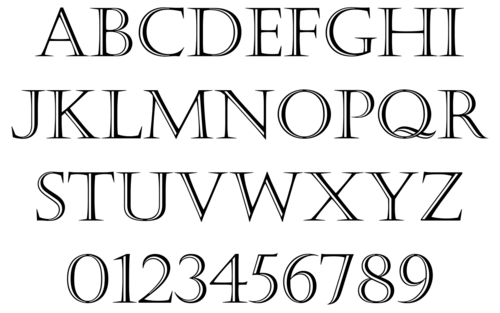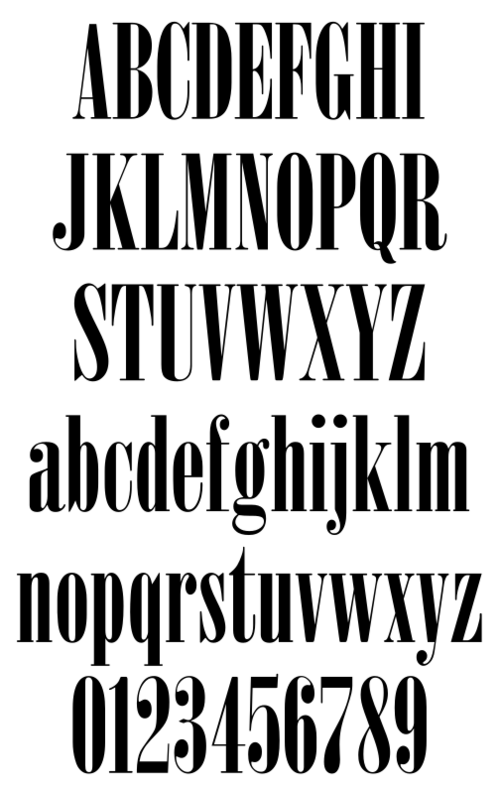
Monotype フォントはMonotype 社によって開発されました。この名前は 3 つの会社で使用されています。そのうち 2 つの会社は、印刷業界の「ホット メタル」または鉛活字にルーツを持っています。コンピューター、オフセット、写真システムが主流になって市場が変化しても、これらの会社は適応できませんでした。これらの会社は次のとおりです。
3 番目の会社は、コンピューターで使用するフォントを製造しています。
- モノタイプイメージング株式会社
後者の会社は、ある意味では英国のモノタイプ工場の後継者です。同社はオリジナルのデザインの権利を保有し、後に他の情報源からさらに多くのデザインの権利を取得しました。生産アーカイブの残骸とマシンの残骸は、英国ロンドンの活字博物館にあります。そこでは、オリジナルの母型に今でもアクセスでき、古いマシンの部品を注文できます。コレクション自体は大英科学博物館の所有物です。建物はもはや科学博物館の所有ではなく、修繕状態が非常に悪く、新しい所有者は建物を他の用途に使用しようとしていたため、活字博物館の存続が危ぶまれました。活字博物館は閉鎖され、すべての機器は国立公文書館に保管されています。[1]
熱い金属
上で述べた最初の 2 つの企業は、名前とシリアル番号で識別される多数のフォントを制作しました。その書体デザインは最終的に非常に評判が良くなり、「Monotype」ブランドは高品質と信頼性の代名詞となりました。[2]
彼らの名の下に、タイポグラフィの初期の歴史的な文字デザインに関する多くのタイポグラフィ研究が行われてきました。Garamond、Baskerville、Bodoni、Bembo、Caslonなどの多くの書体の文字を含む多くの文字が「復活」として制作されました。
両社の大きな違いは、アメリカのフォントが英語のフォントと一致しないことです。同じ名前の文字でもほとんどの場合デザイナーが異なり、外観や実装が異なります。識別番号はすべて一致しているわけではありません。
2 つの会社の母型は、深さ、母型内の画像、実装、およびサイズの点でも異なります。たとえば、アメリカの母型は 0.01 インチ (0.25 mm) 浅く、その結果、0.918 インチ (23.3 mm) の文字を印刷するには、アメリカの鋳造金型の内部を高くする必要があります。これは、2 つの Monotype 社が世界市場を分割するために取った多くの対策の 1 つです。たとえば、アメリカの会社は南北アメリカ大陸とカナダの市場にサービスを提供しました。イギリスの会社であるサルフォーズの Monotype Corporation Ltd. は、インド、アフリカ、およびアジアに多くの顧客を抱えていました。これらの国々向けに、ヘブライ語、ジャワ語、サンスクリット語、シンハラ語、タイ語、およびその他の言語の印刷用に、多くの非ラテン文字書体が作られました。
モノタイプ社の組版鋳造機は、1 片の活字で構成されたテキストを含む、すぐに使用できる組版ページを生成しました。この機械は、さまざまな幅のスペースを追加して行を揃え、行を塗りつぶしました。これらのエンディング マシンは、紙のリボンで制御されました。キーボードでテキストを入力するのは手作業で、鋳造よりもはるかに時間がかかりました。組版鋳造機には、少なくとも 3 つの個別のキーボードのリボンが必要でした。最終的な組版の修正は、可動式活字を交換するだけで済みました。Linotypeマシンのように、行を再鋳造する必要はありませんでした。
これらの組版鋳造機は、最大 14 ポイント パイカまたはディドー フォント幅の文字を生産できました。「大型組版」のカスタマイズされた機械と金型は、最大 36 ポイントの組版を提供できました。マトリックスはそれに応じて大きくなり、金型ケースには 1 つのアルファベットしか収まりません。このため、1 回の機械操作でローマン体とイタリック体の両方の書体の組版を提供することはできず、そのような場合には追加の手作業が必要でした。
手組版用の活字もモノタイプ機で鋳造されました。36 ポイントまでのすべての文字と罫線は、大型組版機で鋳造できました。もう 1 つの機械は「スーパー キャスター」または「スープラ」で、これは 1 つの活字を鋳造できました。改造後は、レグレット、装飾、類似のデザイン、および 72 ポイントまでの文字など、印刷所で必要なあらゆる素材の鋳造にも使用できました。14 ポイントから 36 ポイントのサイズ用のインサートを備えた鋳型がありました。さらに大きい 42、48、60、および 72 ポイントのサイズには、別の活字鋳造が使用されました。異なる活字要件ごとに機械を再構成する必要がありました。
ユニット配置
熱鉛モノタイプ活字の幅は、セット単位で表されます。アルファベットの最も幅の広い文字 (通常は大文字の「W」) は、1/4 パイカ ポイントで測定され、単位はこの幅の 1/18です。12セットの例では、単位幅は次のように計算されます。
- 1 パイカ = 1 ⁄ 6インチ
- 1 パイカポイント = 1 ⁄ 12 × 1 ⁄ 6インチ = 0.013889 インチ
- 1 ユニット 1 セット = 1 ⁄ 18 × 1 ⁄ 12 × 1 ⁄ 6 = 1 ⁄ 1296インチ = 0.000771605 インチ
- 1 ユニット 12 セット = 12 ⁄ 1296 = 0.00925926 インチ
すべての文字は、セットの単位の整数倍の幅を持つように設計されています。5、6、7、8、9、10、最大 18 またはそれ以上。
- 5 個 12 セット = 0.046296 インチ
- 6 ユニット 12 セット = 0.055555
- 7 ユニット 12 セット = 0.064815
.....
- 18 ユニット 12 セット = 0.1667 インチ
イギリスとアメリカのマニュアルでは、パイカのサイズが異なります。新しいパイカは 0.1660 インチです。ヨーロッパ本土では、マニュアルのすべてのウェッジと表は「古い」パイカ = 0.1667 インチに基づいており、それらのウェッジは追加の大文字 E (= 英語) で識別できます。そのため、さまざまなマニュアルの表にわずかな違いがあります。ただし、実際には、これらの違いは非常に小さいため、新しいパイカに基づく S5-E ウェッジまたは S5 ウェッジで鋳造すると、ほとんど違いはありません。すべての文字は、セットの単位の整数倍の幅を持つように設計されています。
たとえば、A=14、B=13、C=14... a=8、b、d、h、k、n、p、q=10、c=8... これらの幅のリストは「単位配置」(UA) と呼ばれます。異なるフォントが同じ UA を持つ場合があります。フォント デザインによっては、Lutetia (書体)やJan van Krimpenの他のフォントのように、ポイント サイズごとに単位配置が異なる場合があります。これらの UA は、マトリックスが単位幅によって行にソートされるマトリックス ケースのレイアウトに不可欠です。さまざまな「単位配置」には番号が付けられています。
長いディセンダーと短いディセンダー
gjpqy ij の文字はディセンダーです。イタリック体では、fと「長い s」もディセンダーです。
古いフォントの多くは、主に新聞のコラムで使用することを想定していました。Times New Roman が良い例ですが、他にもたくさんあります。このようなフォントでは、すべてのテキストを同じ行間隔で設定できるように、ディセンダーは可能な限り短く保たれていました。ただし、高級作品用のフォントの多くでは、ディセンダーの長いバージョンも用意されており、鋳造時にライニングを調整してそれらに対応する必要がありました。
活版印刷
この技術では、活版印刷用のフォントのデザインを調整する必要があります。その理由は、活字が紙にある程度力を入れて印刷され、活字のインクが文字の端まで押し出されるためです。したがって、文字の中央は端よりも少し薄く印刷されます。その結果、「ビードエッジ」と呼ばれるものになります。活字の表面だけでなく、その周りのベベルにもインクが付くため、ビードエッジはさらに強調され、拡大鏡で簡単に見ることができるように、印刷された書体の視覚効果にも貢献します。[3]
印刷されたビーズの縁と明るい中心は、カリグラフィーの書体を連想させます。また、活版印刷では、印刷に適した、多くの場合より高価な紙の種類を幅広く選択できます。
コンピュータの調整
ますます多くの印刷会社が活版印刷からオフセット印刷に移行したため、「ホット メタル」会社が生産を停止した後、 [いつ? ]ランストン モノタイプがアメリカで最初にそれを行ったため、フォント デザインはコンピューターでの使用に合わせて調整する必要がありました。ユニット配置内の文字の幅の固定関係がしばしば不利に感じられるため、古いホット メタル文字と比較すると違いがあります。この問題については、たとえばJan van Krimpenによって長い間議論されてきました。
鉛活字のデザインは、印刷中に鉛活字にかかる圧力によってインクが横に押しつぶされ、紙に印刷される文字の最終的な外観が鉛活字の表面よりも広くなるため、調整なしではコピーできません。この余分な幅は、文字の周りのすべての場所で同じではありません。これは、使用される紙の表面、圧力、印刷機の種類 (シリンダーかプラテンか)、およびその他の多くの要因によって異なります。
デジタル時代初期の多くのデジタル フォントには、この特徴的な欠陥があります。金属表面が単純にコピーされたため、印刷されたページの色が薄すぎます。オフセット印刷やその他の最新の印刷技術では、プレート上の書体と印刷された文字の書体は、はるかに密接に一致しています。オフセット印刷では、主にコーティングされた紙を使用することも影響します。オフセット印刷やコンピューター印刷用に調整せずに鉛文字の表面を単純にデザインするだけでは、良い結果は得られないため、書体設計プロセスでは、これらすべてを考慮する必要があります。
書体一覧
以下のアルファベット順のリストは、主に英国の「ホット メタル」Monotype 社が製造したフォントに関するものです。以下に記載されている番号は、英国の「見本ブレード」、小冊子「Monotype 情報ブック」の 4 版、およびロンドン タイプ ミュージアムからの追加情報からのものです。
1960 年代には、多くの Monotype フォントが製造中止になりました。パンチの作成元となったオリジナルの「パターン」、パンチ、および残りのマトリックスの在庫はすべて破棄されました。フォントは、さまざまな印刷業者が所有していたマトリックスを除いて姿を消しました。これらのフォントのサンプル シートは特に見つけにくく、多くのコレクションに欠けています。
少数のアメリカの文字デザインがリストに追加され、「Am」とその番号で指定されています。アメリカの文字母型はイギリスの文字母型とは異なります。アメリカの文字母型は、0.001 インチ (0.025 mm) 浅く彫られています。その結果、アメリカの鋳型は、イギリスのサルフォード工場の鋳型と比較して、その分だけ内部が高くなっています。その結果、イギリスの鋳型にアメリカの文字母型を使用すると、低い文字が生成されます。イギリスの文字母型をアメリカの鋳型に使用した場合、フランスの高さの文字が生成されます。
- Univers was developed in cooperation with the French type foundry Deberny & Peignot.
- It was possible to cast characters in lining with the character bought in France.
- 693: Univers Bold Roman/italic
- composition matrices: UA.486 = 5D-12D, extra &: S16511, S16512, superior: L225,[115]
- display matrices:
- 694: Univers Bold Condensed Roman/italic
- 692: Univers Bold Expanded Roman
- composition matrices: UA.491 = 6D-10D, extra &: S16511, superior: L228,[46]
- display matrices:
- 696: Univers Extra Bold Roman